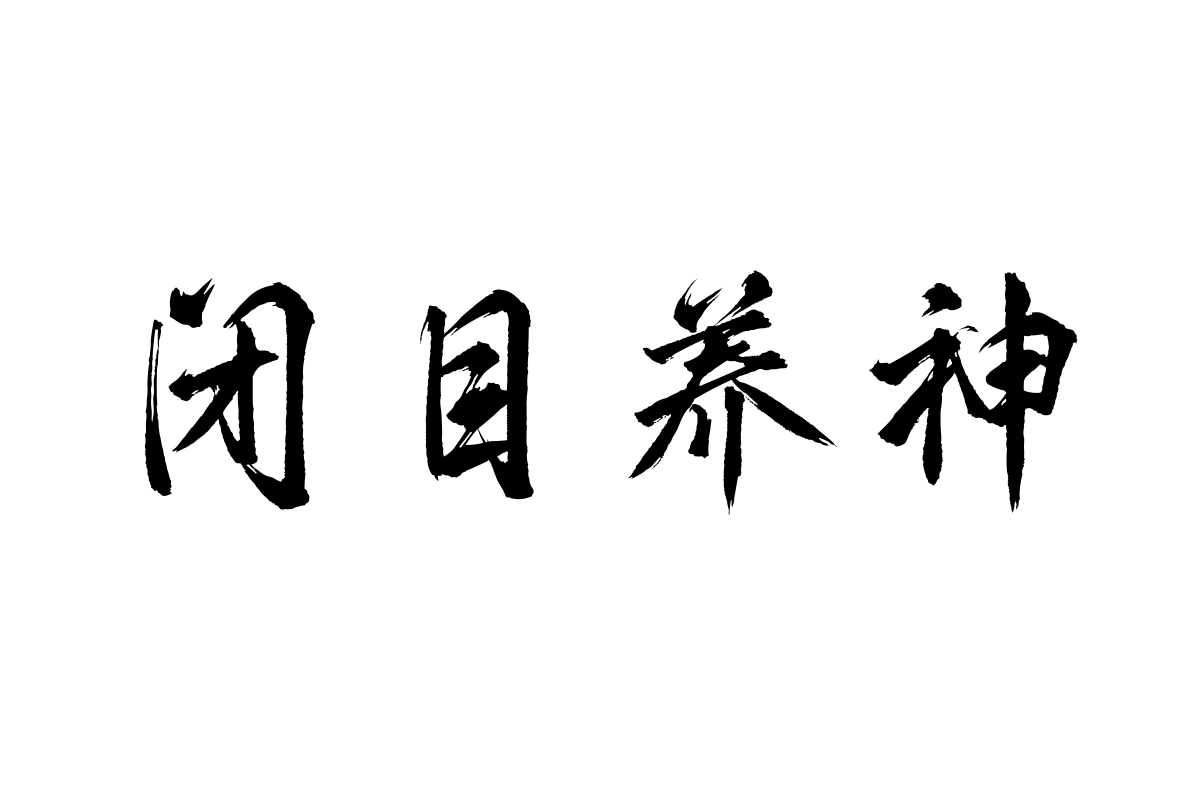
汉仪轻舟行字体是一款具有现代感的中文字体,它以简洁、流畅的线条为主要特点,给人一种轻松愉悦的感觉。这款字体适用于各种需要表达轻松、自由氛围的场合,如广告设计、网页设计、包装设计等。
汉仪轻舟行字体的特点如下:
1. 笔画流畅:字体的笔画线条流畅自然,没有过多的装饰性元素,使得整体看起来更加简洁大方。
2. 字形美观:字体的字形结构紧凑,线条粗细适中,使得整个字体看起来美观大方。
3. 适应性强:这款字体适用于多种场景,无论是在正式的商务场合还是在休闲的娱乐场合,都能很好地融入其中。
4. 易读性强:字体的笔画线条清晰,使得文字的阅读起来更加容易,提高了信息的传递效率。
总的来说,汉仪轻舟行字体是一款非常适合现代设计风格的中文字体,无论是在商业设计还是日常生活中,都能为作品增添一份独特的魅力。